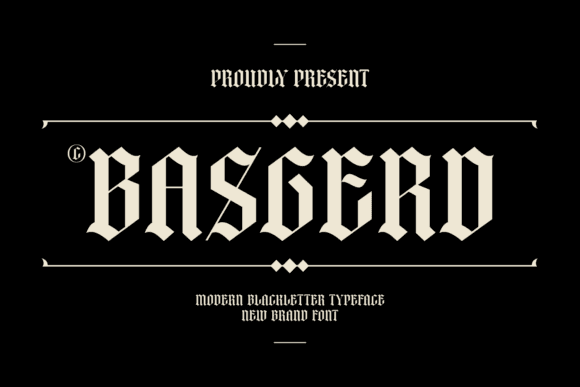
Fonte Basgerd para projetos de artesanato, logotipos e impressão.
Fonte Basgerd
Basgerd é uma fonte preta ousada e dramática, ideal para criar pôsteres e flyers impactantes com um tema vintage ou gótico. As letras intrincadas chamam a atenção e adicionam um toque único a qualquer projeto. Seja em identidade visual, itens decorativos ou documentos formais, Basgerd confere um caráter atemporal e distinto a qualquer texto.